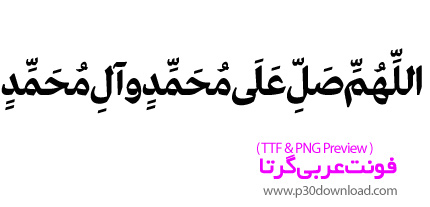
دانلود فونت عربی، فارسی، اردو، انگلیسی گرتا Greta Text Font
شما کاربران گرامی شاهد فونت عربی، فارسی، اردو، انگلیسی گرتا (Greta) با فرمت TTF هستید که میتوانید آن ها را درطراحی های گرافیکی خود به کار ببرید. طراحان و گرافیست های خلاق می توانند از این فونت زیبا در طراحی های خود استفاده کنند.
فونت غریتا با انگیزه و هدف طراحی ایجاد شد. طراح لبنانی این تایپفیس کریستیان سارکس (Kristyan Sarkis) در این فونت شاهکار میآفریند و در فضا و کنتراست فونت استحکامی را به رخ می کشد که برای نوشته های رسمی و جدی بسیار مناسب است. این یک فونت نیست. یک تایپ فیس است. خانواده این تایپ فیس شامل چهار فونت است؛ غریتا تکست عربیک نازک (GretaTextArabicLight.ttf)، غریتا تکست عربیک معمولی (GretaTextArabicRegular.ttf)، غریتا تکست عربیک میانه (GretaTextArabicMedium.ttf) و غریتا تکست عربیک ضخیم (GretaTextArabicBold.ttf). و این یک ویژگی مهم و بسیار خوبی است برای نشر رومیزی. و اصلا همیشه توصیه می کنیم که برای منشورات رسمی بهتر همین است که فقط از یک خانواده فونت استفاده شود و تیتر، میان تیر، سوتیتر، زیرتیتر، روتیتر و متن از یک سبک و یک خانواده باشند.طبیعتا این فونت روزنامهای برپایه نسخ آفریده شده ولی ویژگیها و انحناهای مدرنی و شیکی دارد. ارتفاع حروف زیاد نیست و شیب ملایمی دارد که باعث شده هم طراز حروف لایتن آن گردد. حروف این فونت کاملا بر خط کرسی نشسته اند و این باعث شده برای متون طولانی و ریز روزنامهها دلنشین باشد.
از ویژگیهای خوب این فونت پشتیبانی کامل از حروف فارسی، عربی، لاتین و اردو است. حروف ترکیبی زیادی دارد و اعراب گذاری دقیق و خوانایی دارد. فشردگی بین حروف (کرنینگ) مناسبی دارد و از وضوح بالایی برخوردار است.